「都会的!ワンランク上のおしゃフォント集」の気になる中身をご紹介
何かと重宝するシンプルなセリフフォント:GÜNTERHAUS
ModernとTrasitionalスタイルを使い分けられるセリフフォント「GÜNTERHAUS」。イタリック体収録&多言語対応で、幅広い用途に対応できます。
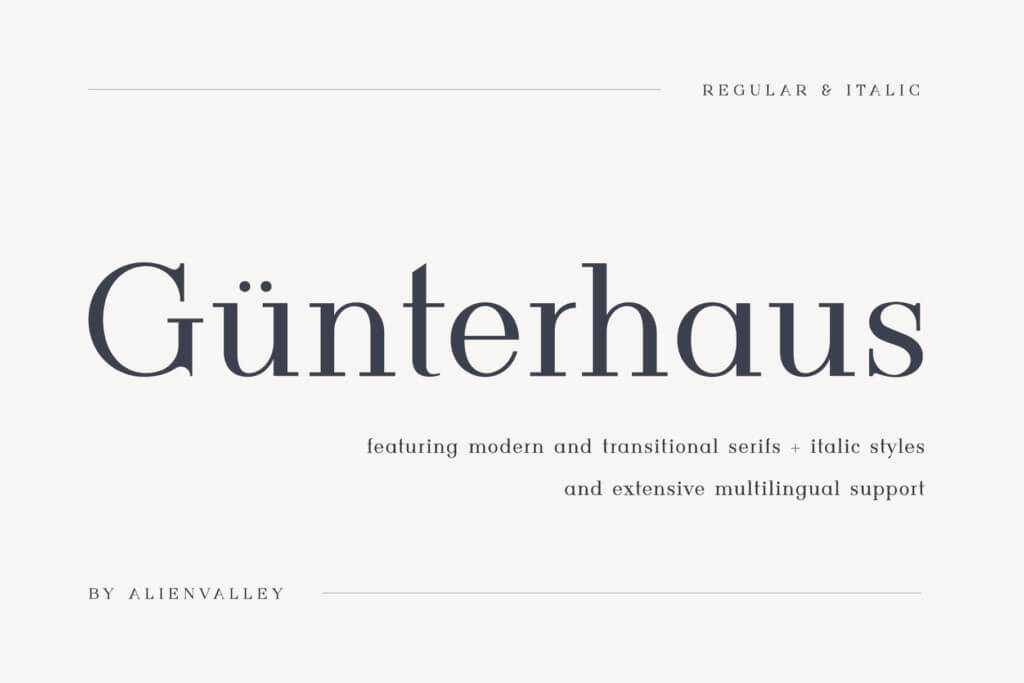
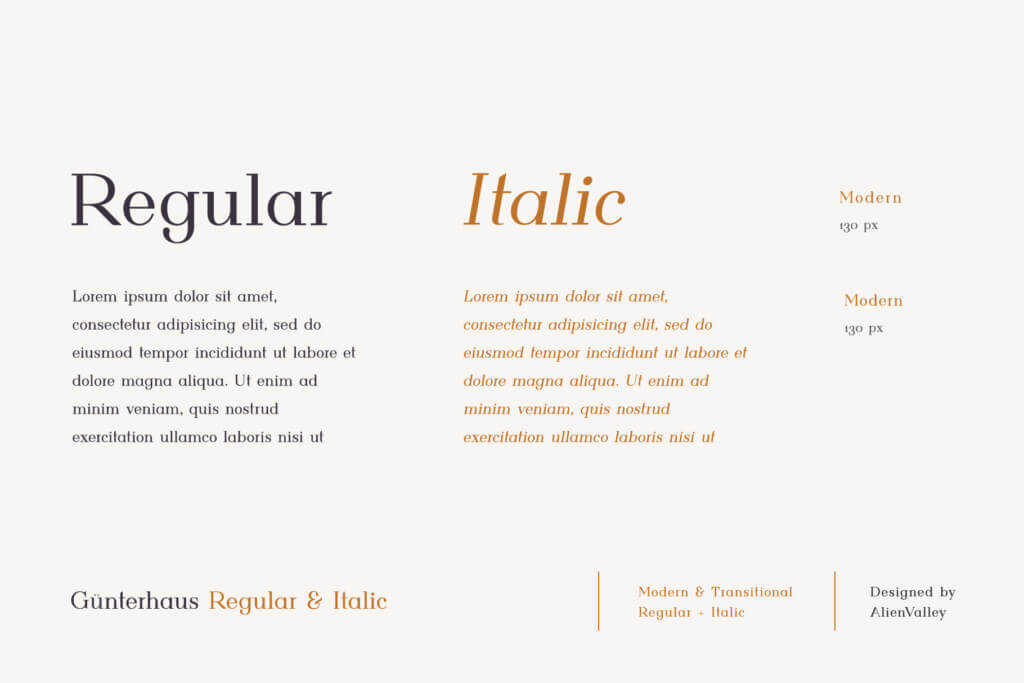
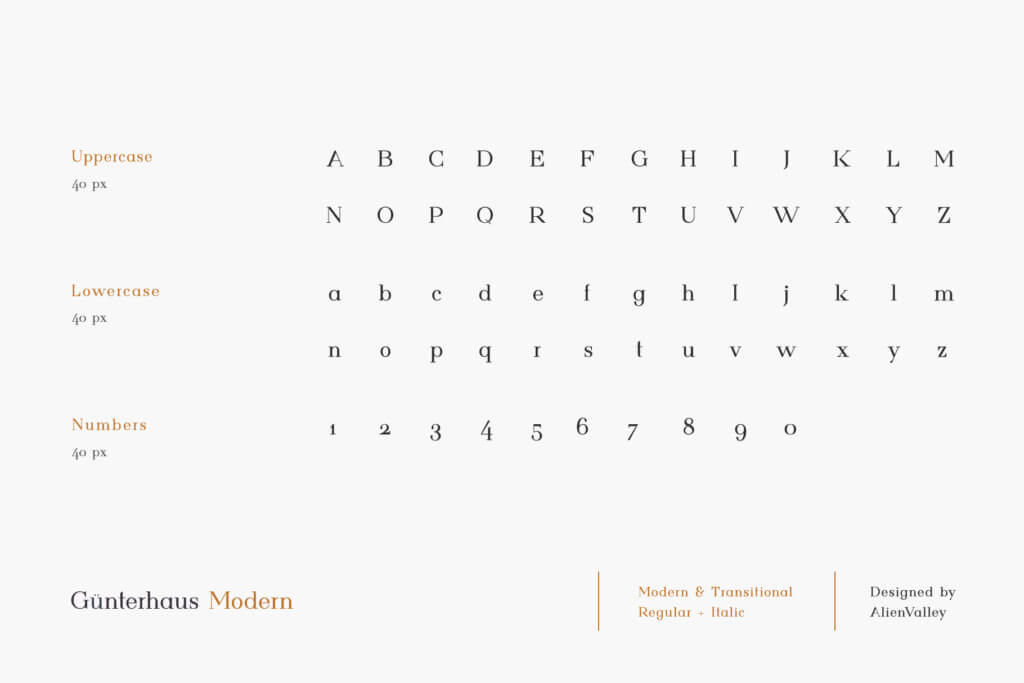
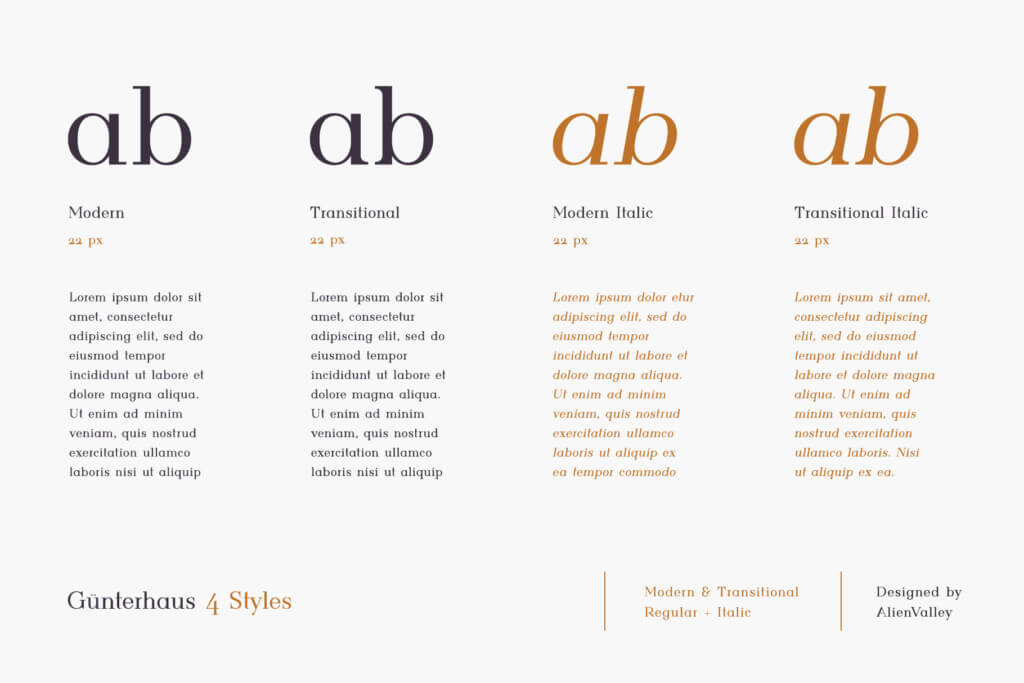
ステンシルフォントもウェイト違いを多数収録:MAJORA PRO
スラブセリフフォントのファミリー「MAJORA PRO」は、ウェイト違いを多数揃えたステンシルフォントも入った珍しいセット。デザインのアクセントに、ぜひ持っておきたいフォントファミリーです。
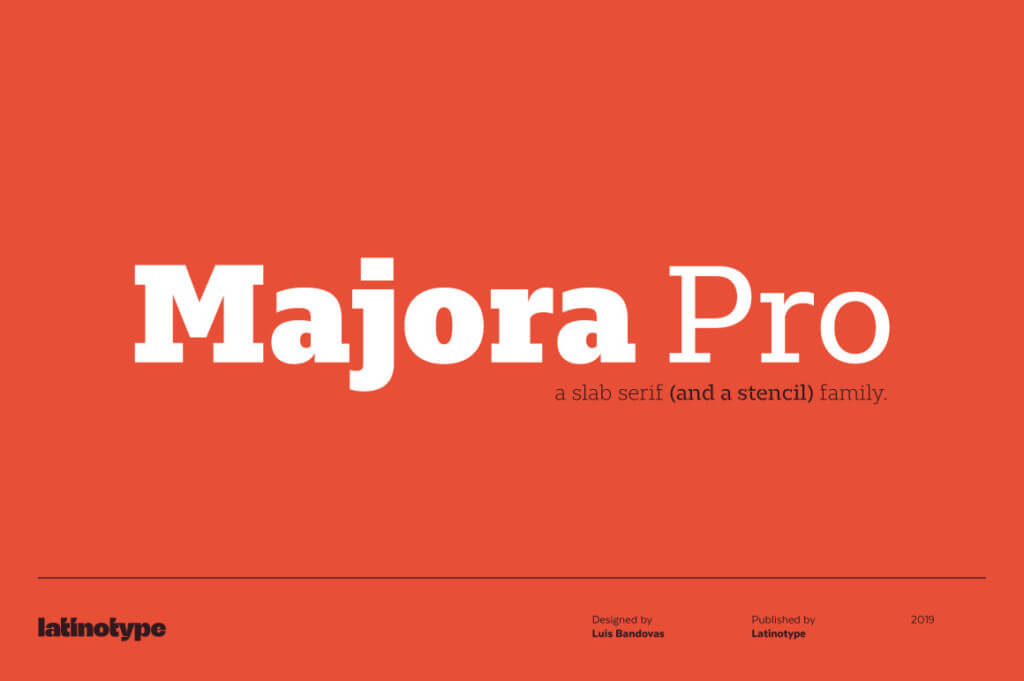
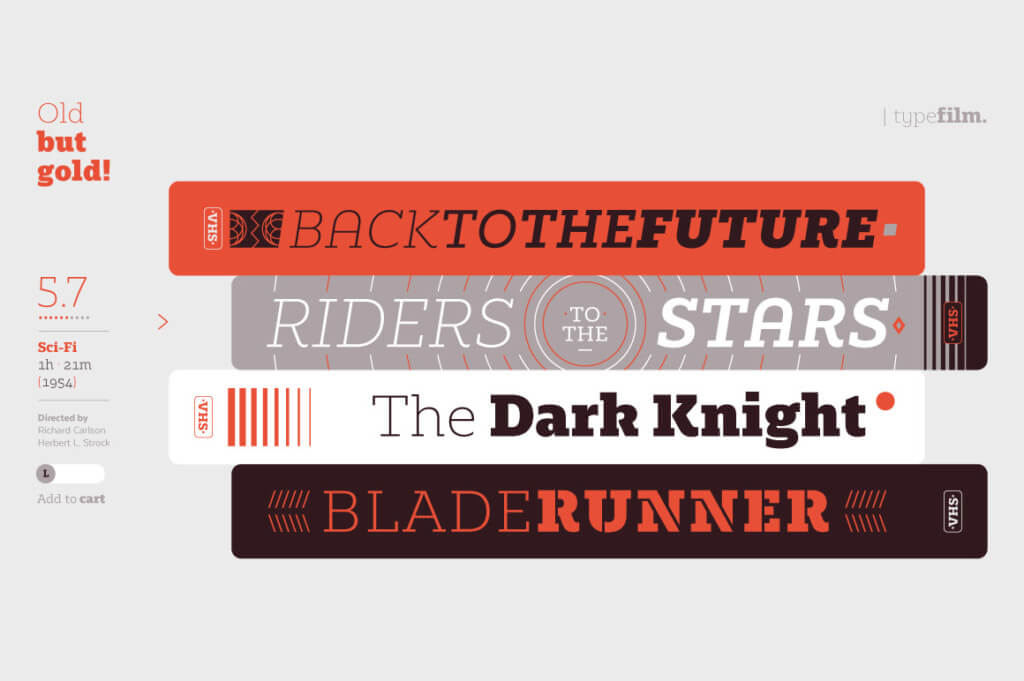
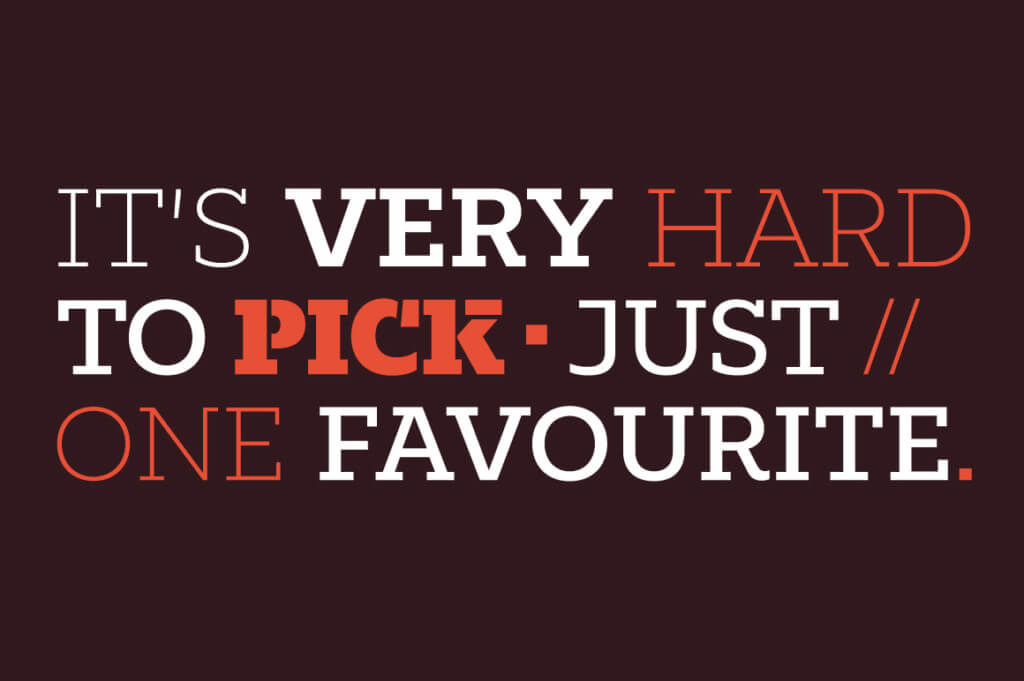
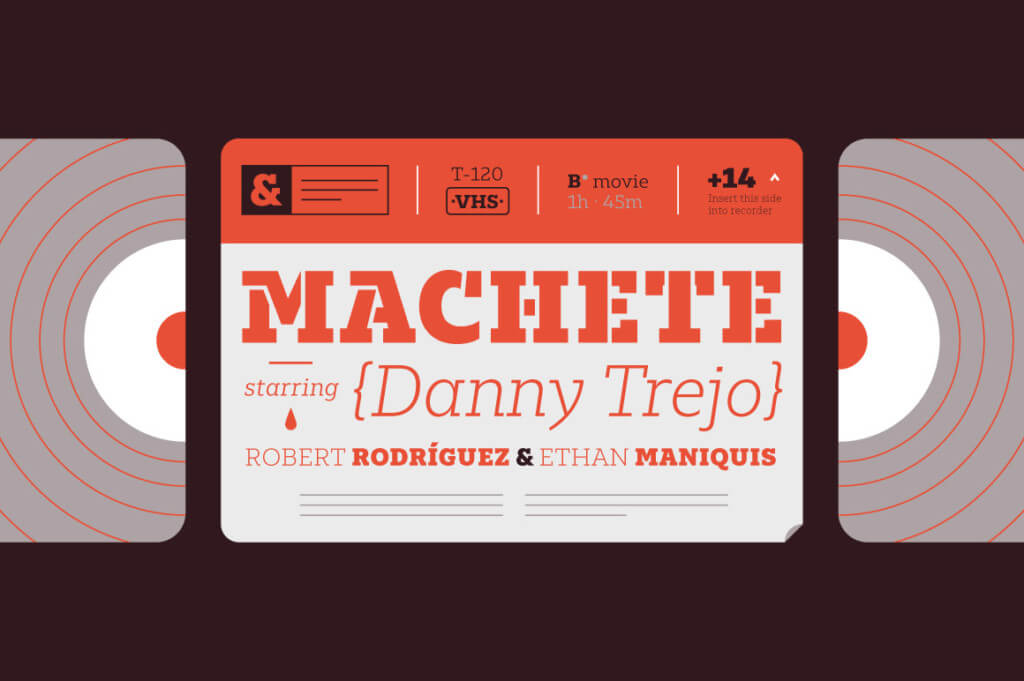
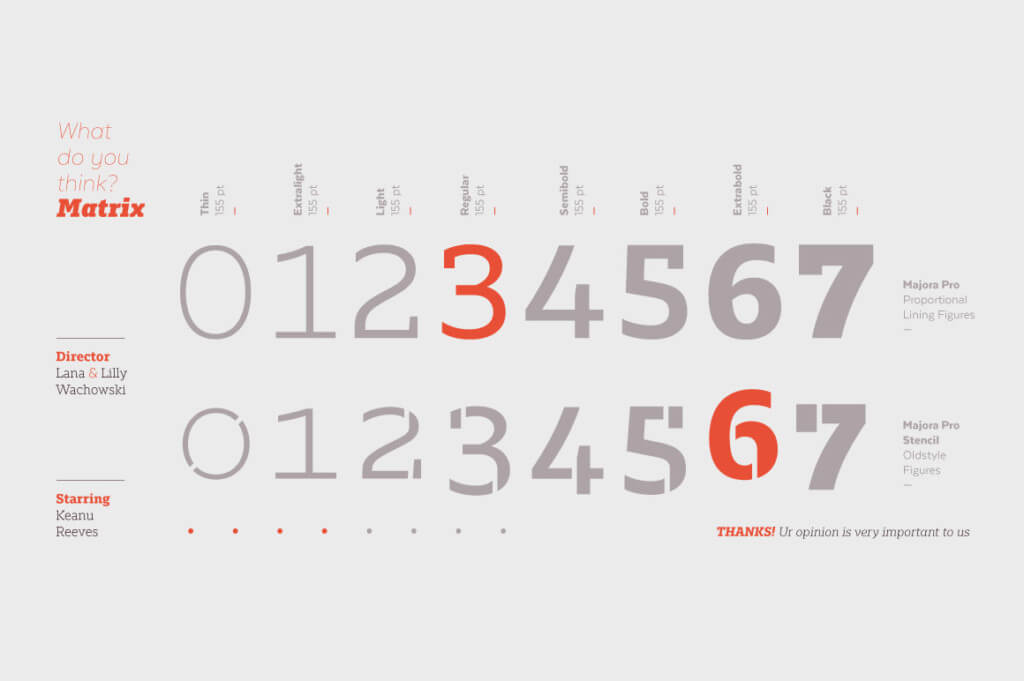
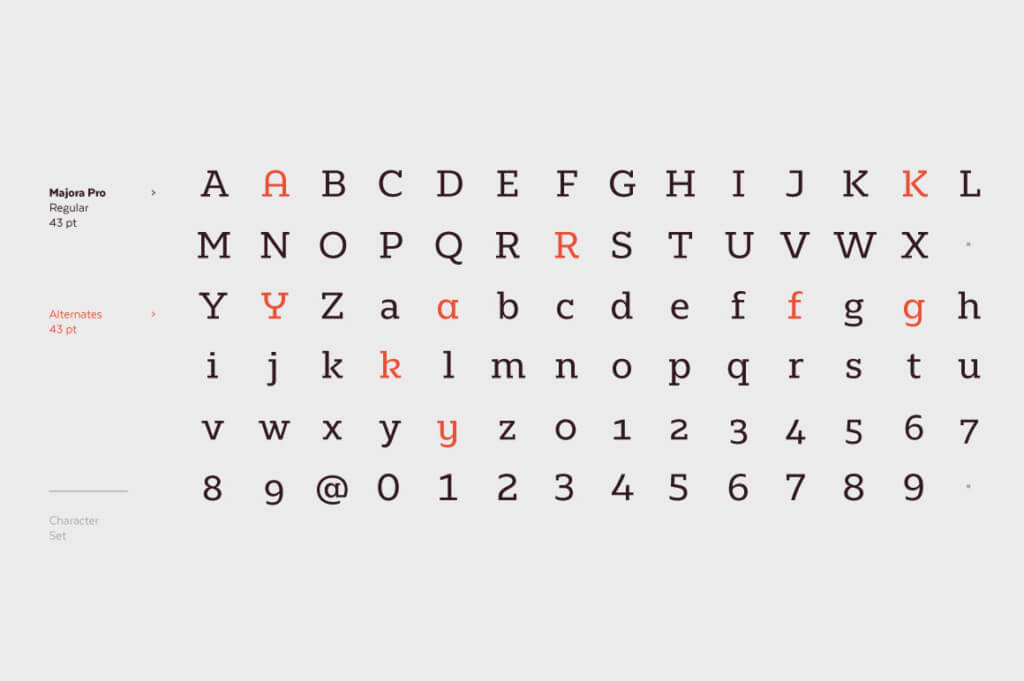
エレガントなデザインが即完成!MODERN SYMPHONY
結婚式の招待状やレストランのメニューなど、エレガントな雰囲気にしたいデザインにオススメの「MODERN SYMPHONY」。セリフフォントとスクリプトフォントがあらかじめセットになっているので、フォントの組み合わせに迷わずデザインが始められます。
2020年リリースの40スタイル収録フォント:GROLD ROUNDED
Groldというフォントに丸みを持たせた「GROLD ROUNDED」は10種類のウェイトをそろえたデザイナーお助けフォント。2020年登場の新しいフォントをいちはやく揃えましょう。
嫌味のないクリーンなデザインフォント:CHERIONE
さりげなくデザインにこだわっている印象を与えられる「CHERIONE」は、リガチャ(合字)が秀逸なフォント。画像のようにおしゃれなロゴを短時間で作りたい時にも大活躍すること間違いなしです。